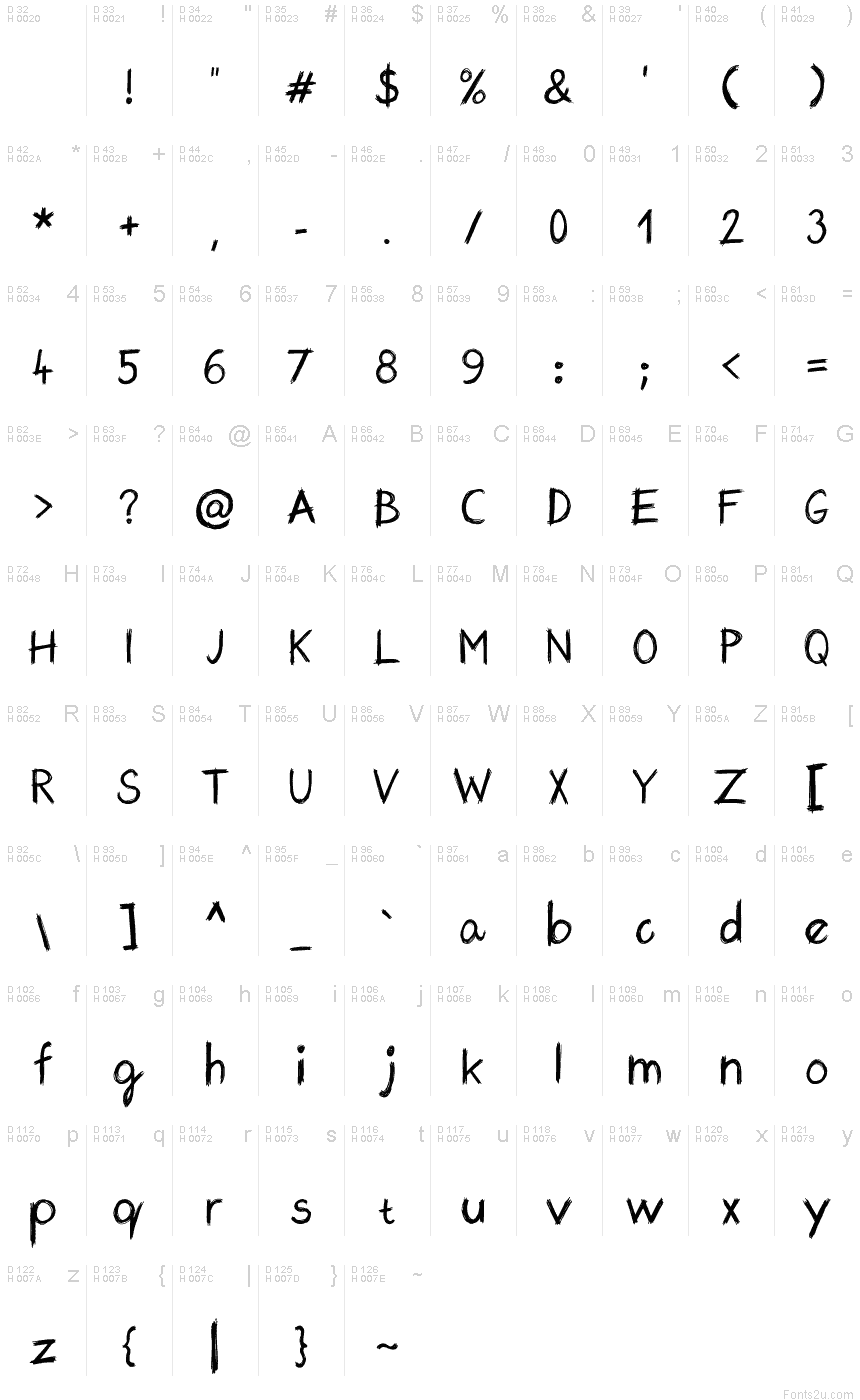
F2U Scratch od Fonts2u.com to darmowy krój pism ekspozycyjnych o porysowanym charakterze pędzla, z tępymi, pociągniętymi kreskami i celowo zniszczonym wykończeniem. Litery wyglądają na szybko namalowane, z postrzępionymi krawędziami i nierównomiernym naciskiem. Tekstura wydaje się surowa i namacalna.
Jako odręcznie kreślony tytuł może nadawać kształt plakatom protestu, grafikom muzyki podziemnej i odzieży streetwearowej z surową postawą DIY. W projektowaniu edytorskim ten sam wytarty styl pędzla sprawdza się w nagłówkach okładek magazynów i wstępach do artykułów poświęconych kulturze punkowej, deskorolce czy miejskim scenom artystycznym.
F2U Scratch